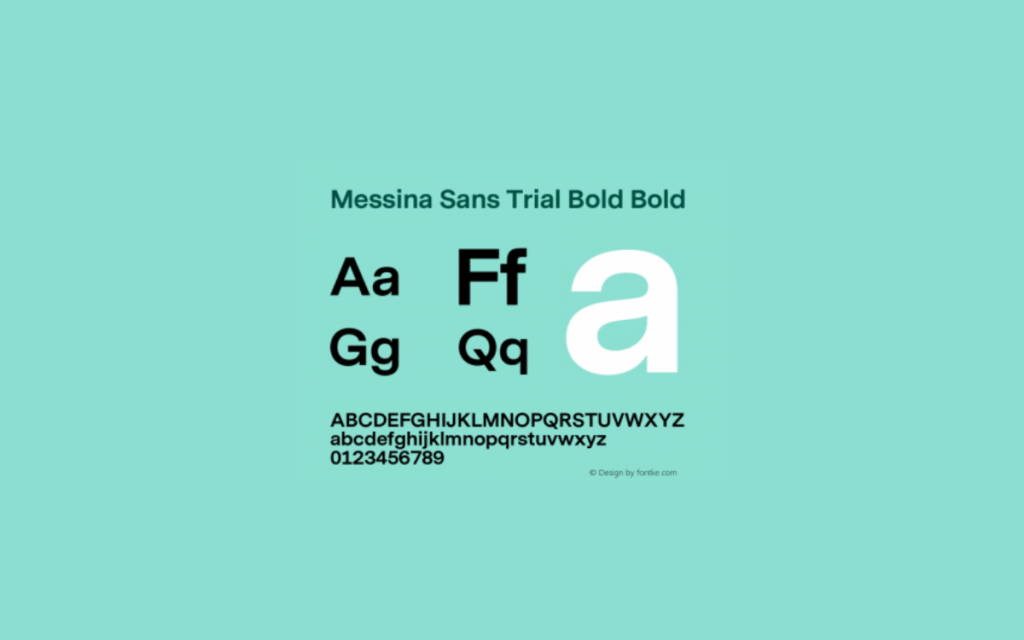
Messina Sans Font Free
Tác giả: Luzi Type
Ngày phát hành: 2015
Phân loại: Đa năng
Messina Sans Font là một kiểu chữ sans-serif hiện đại, thuộc bộ font “Messina” được thiết kế bởi Luzi Type. Messina Sans có phong cách đơn giản, gọn gàng, và dễ đọc, với các đường nét sạch sẽ, không có chân chữ (serif). Font này thuộc bộ font chữ không chân được thiết kế để phù hợp với nhiều ứng dụng khác nhau, từ thiết kế web, in ấn, đến nhận diện thương hiệu. Font chữ tạo nên một bộ công cụ đa năng cho các nhà thiết kế, giúp họ có thể tạo ra các dự án đồng nhất về mặt thẩm mỹ với nhiều phong cách khác nhau.